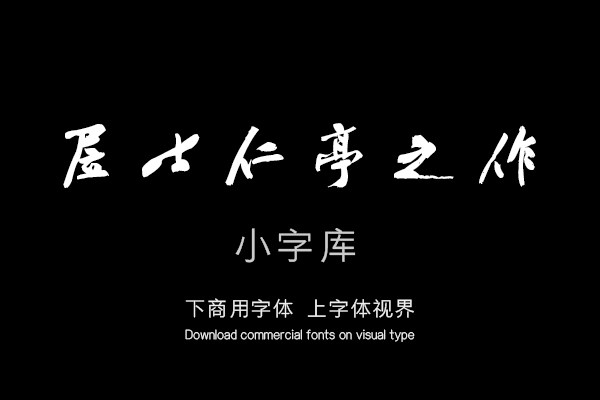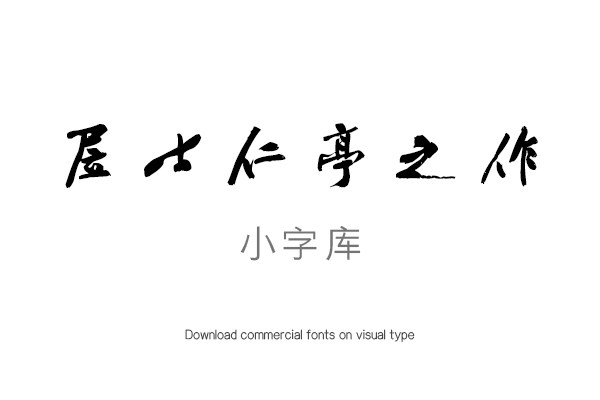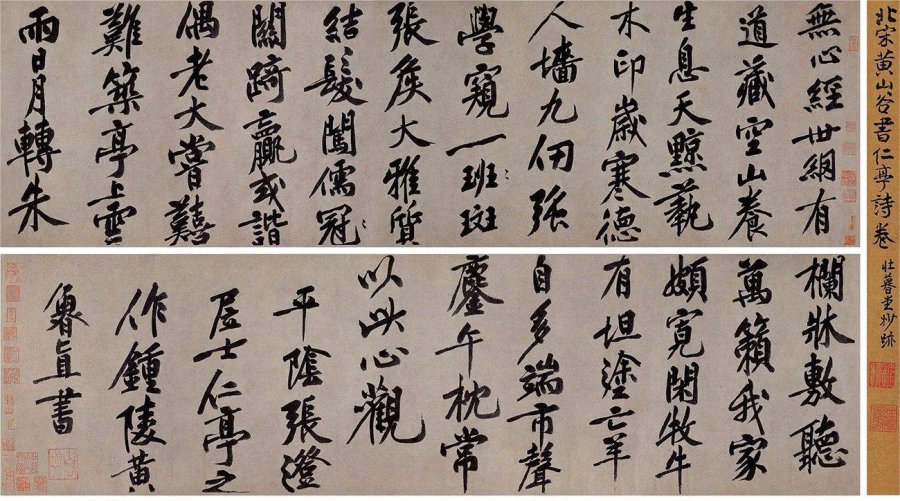
汉标黄庭坚行楷仁亭诗卷
此书法大约作于黄庭坚40多岁。所书内容为黄庭坚自己创作的《平阴张澄居士隐处三诗》之第一章《仁亭》。这卷书法采用的是行楷大字,结字中宫紧收,四面呈放射状,笔画长枪......
无心经世网,有道藏空山。 养生息天黥,艺木印岁寒。 德人墙九仞,强学窥一(班)斑。 张侯大雅质,结发闯儒(冠)关。 奇赢或谐偶,老大尝艰难。 筑亭上云雨,日月转朱栏。 床敷听万籁,我家颇宽闲。 牧牛有坦途,亡羊自多端。 市声鏖午枕,常以此心观。平阴张澄,居士仁亭之作,钟陵黄鲁直书。